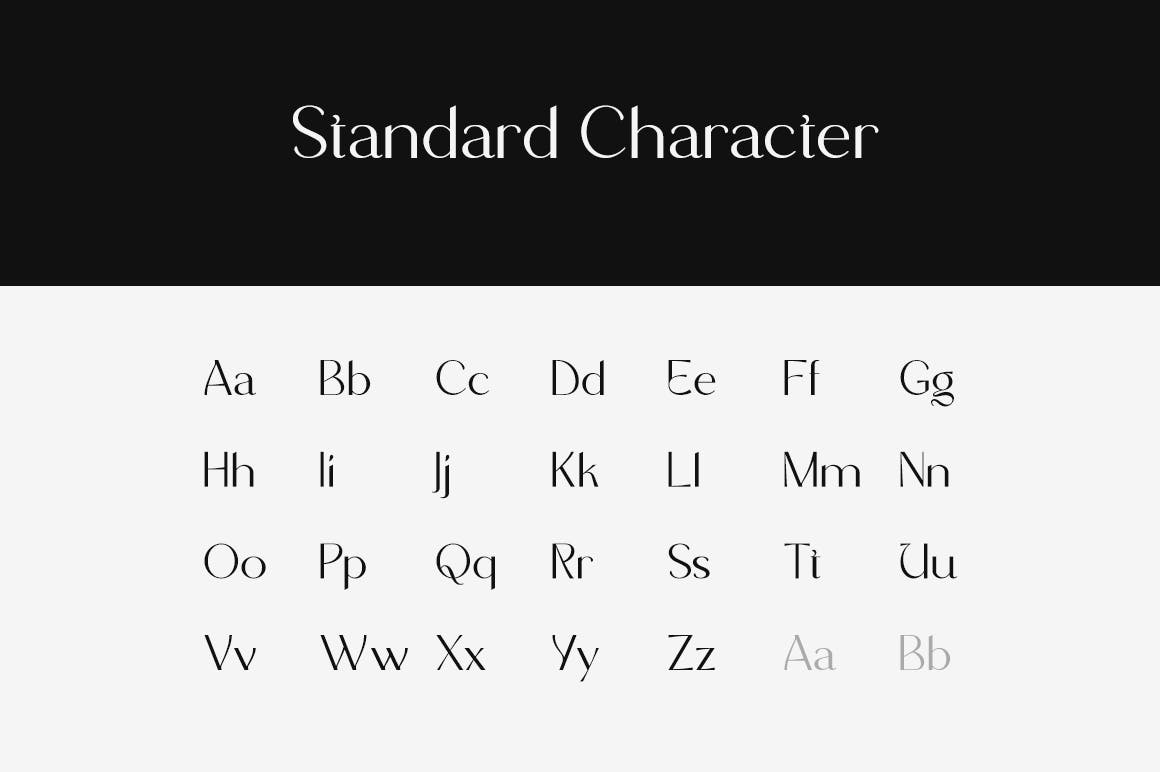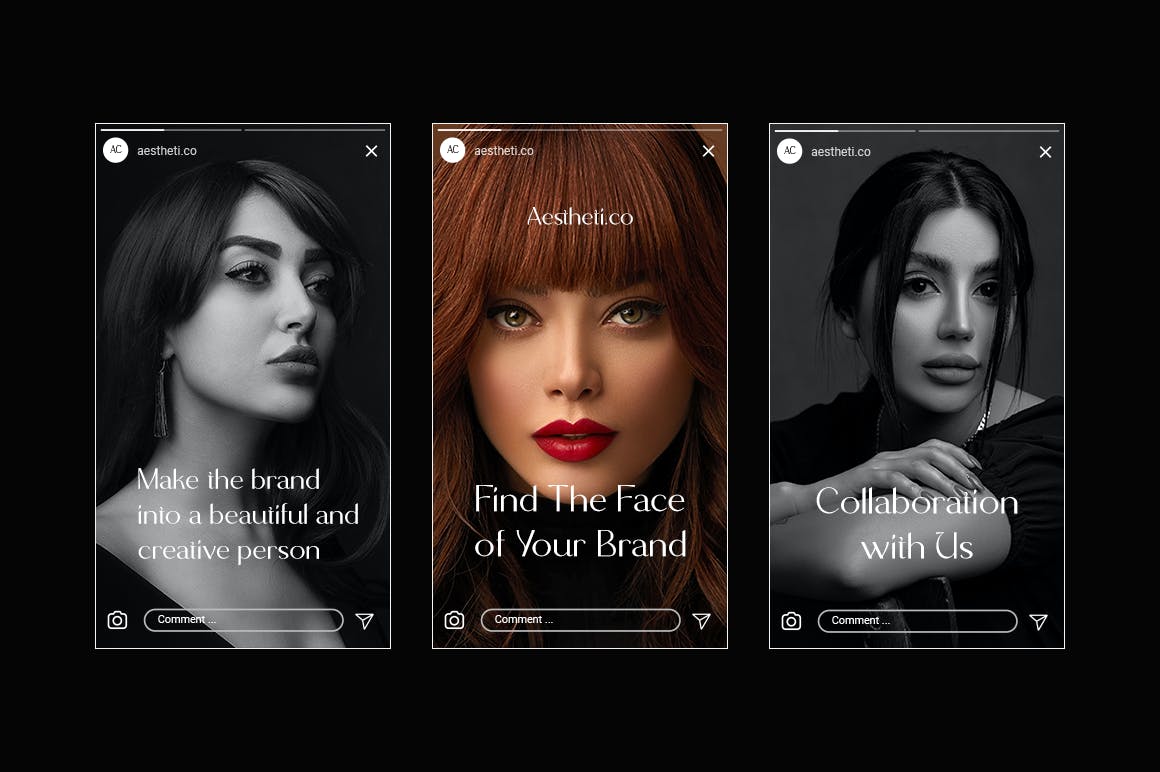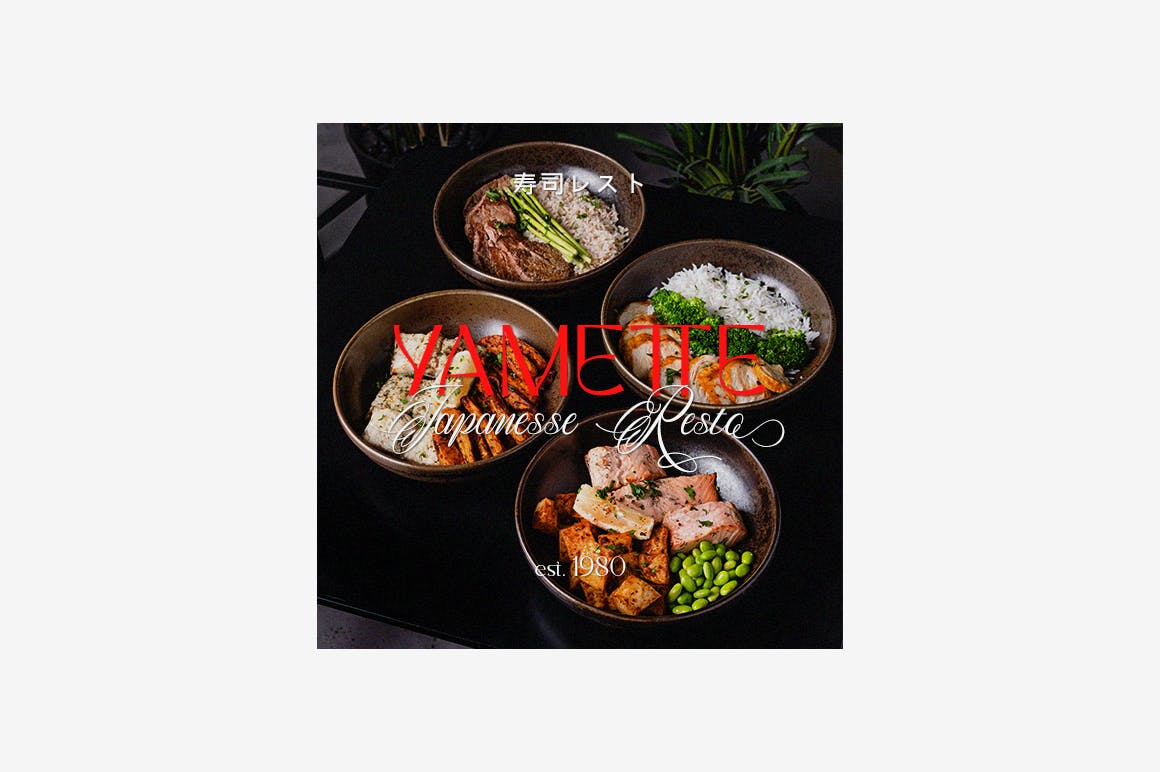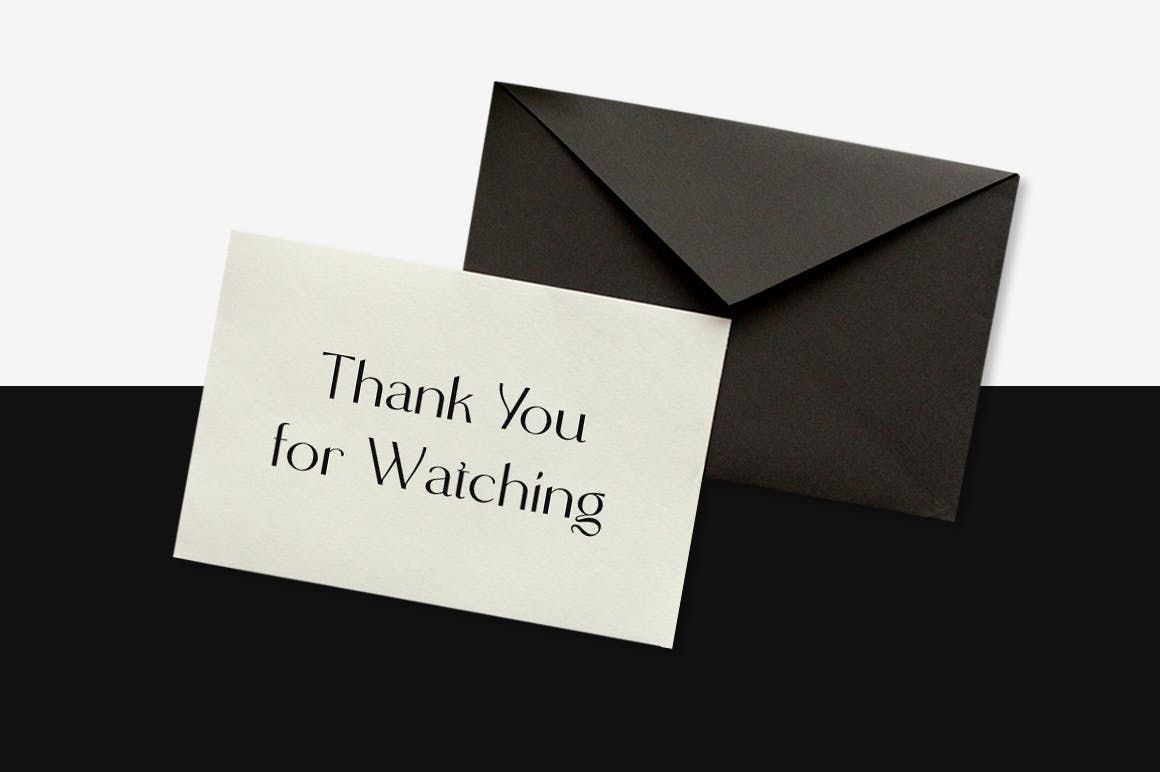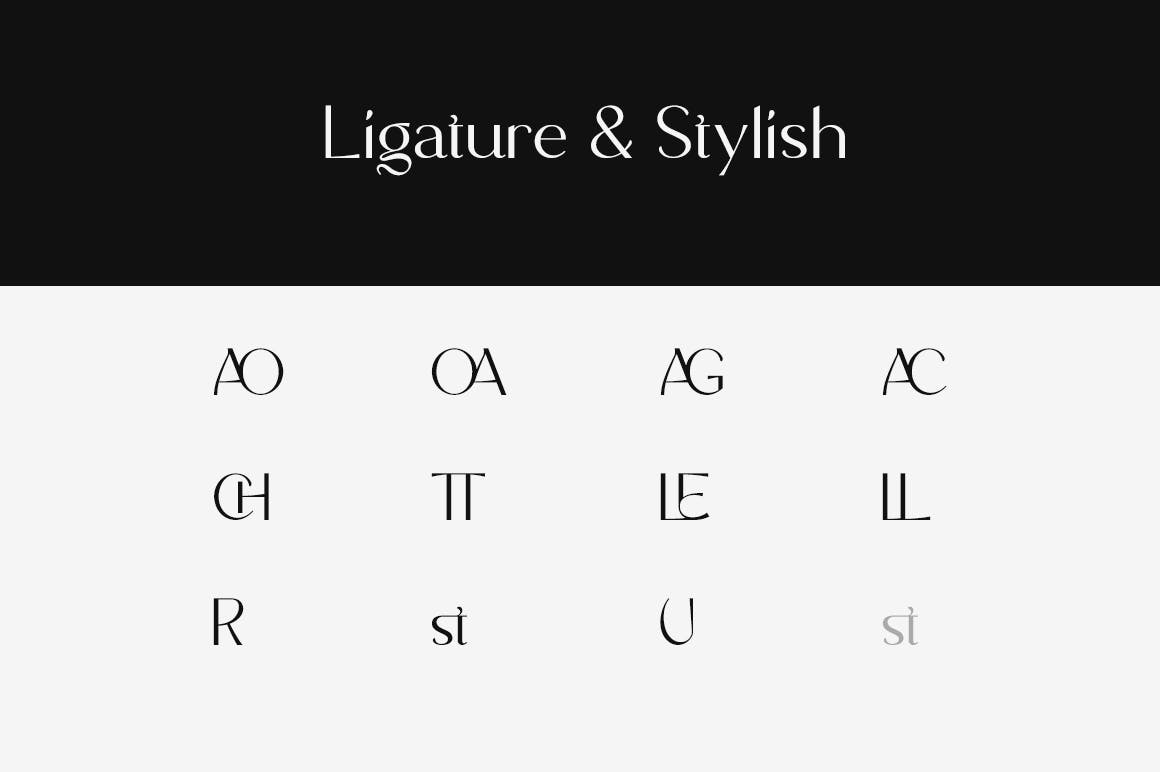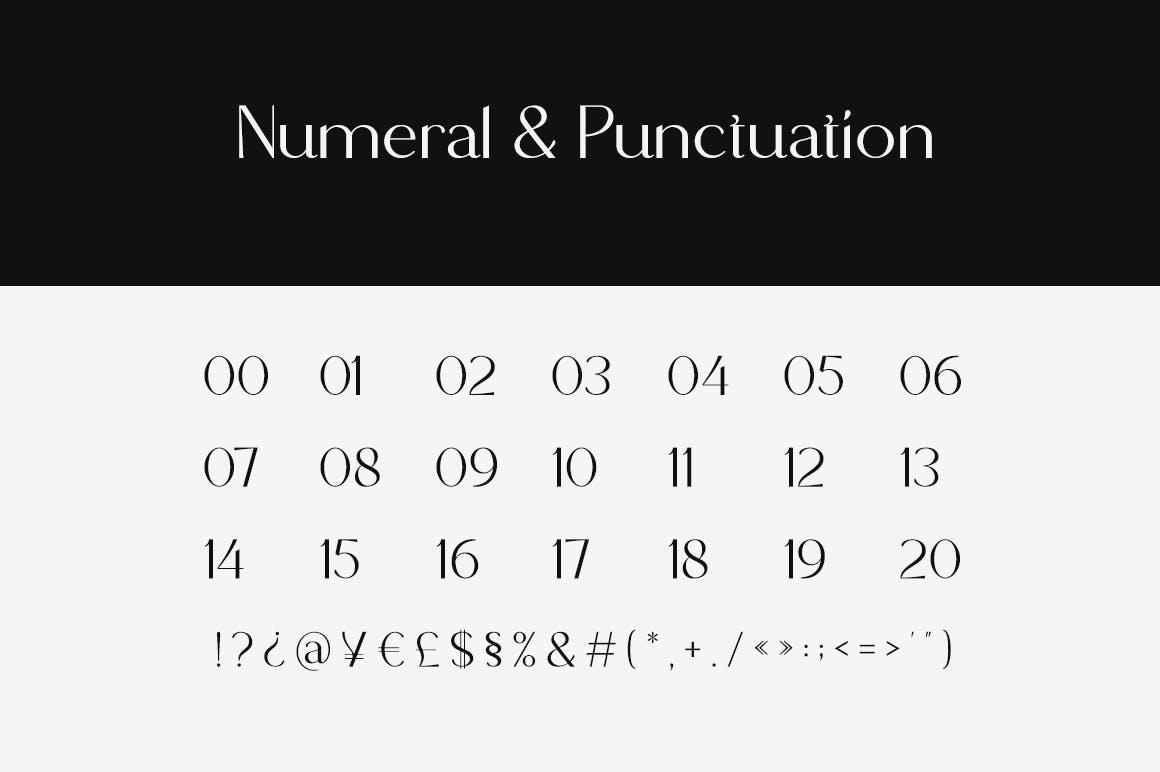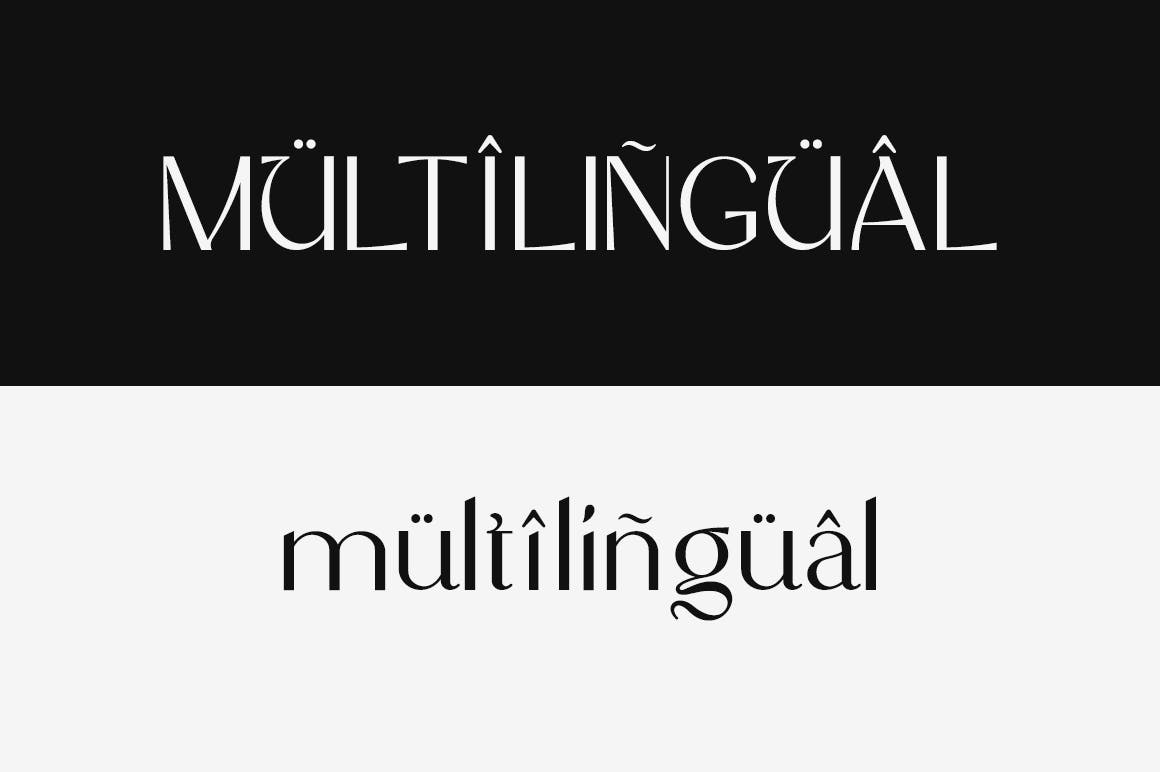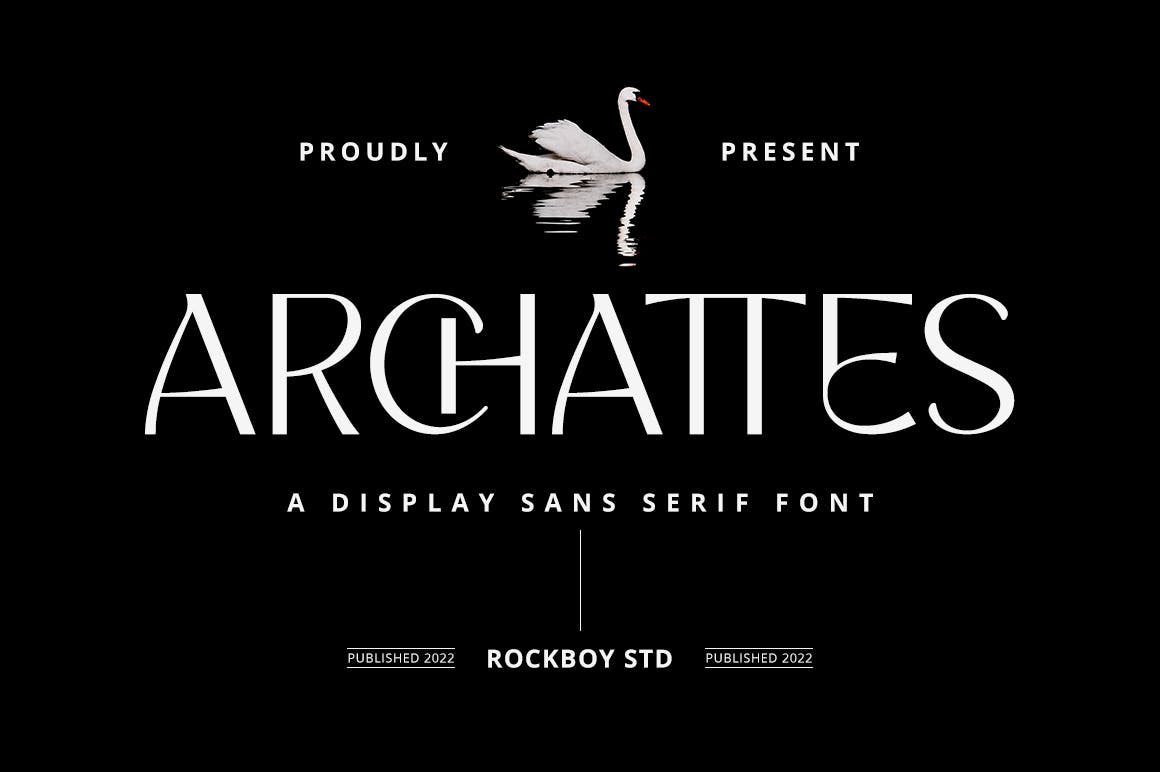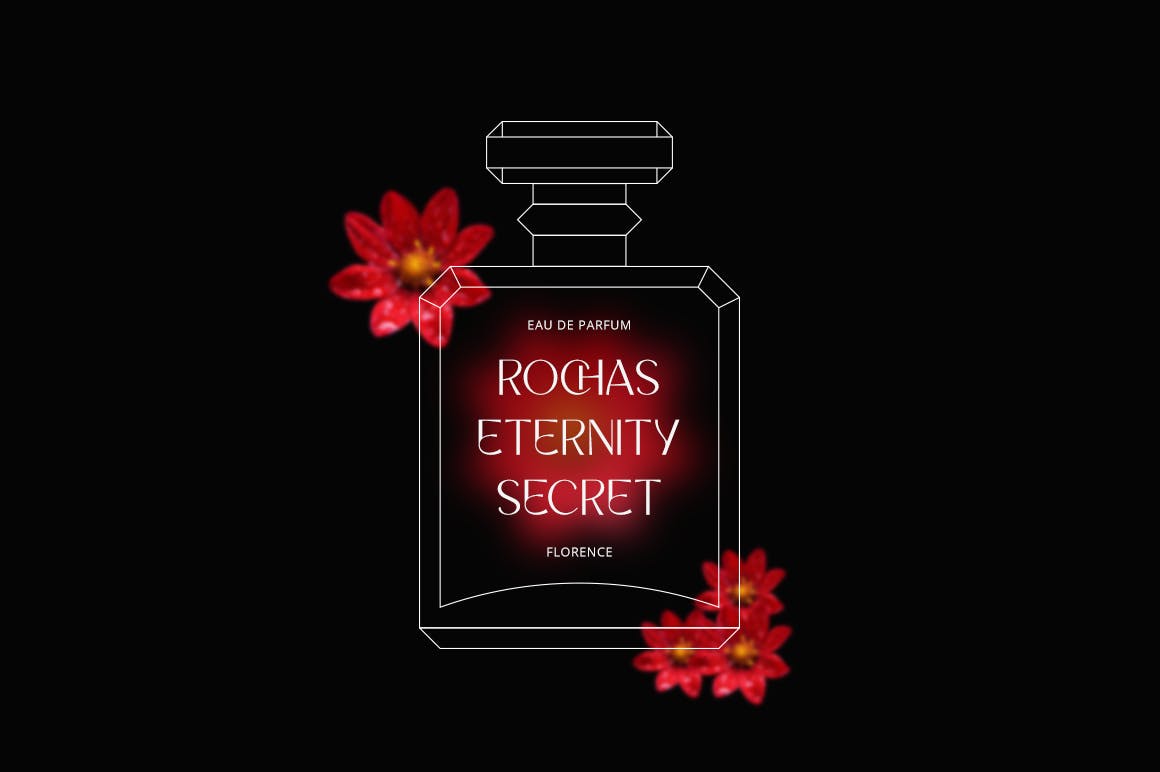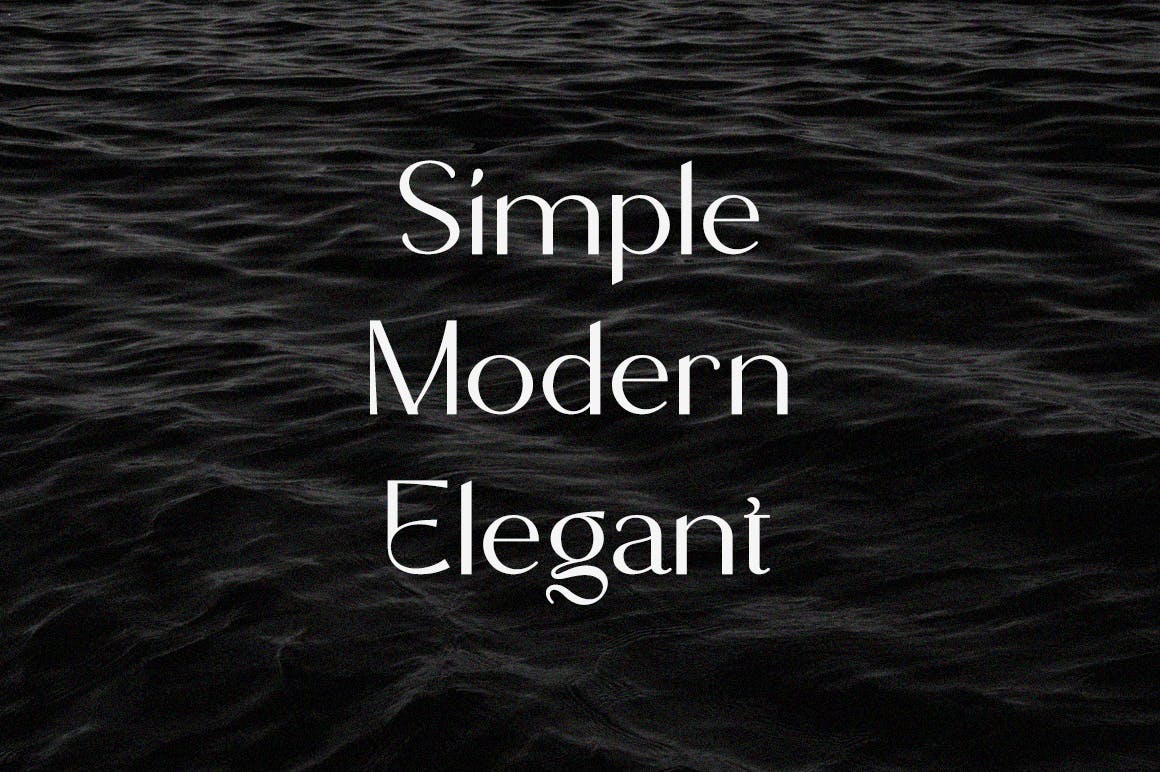
Archattes یک فونت زیبا و شیک از نوع سنس سریف است که میتواند ایدههای خلاقانه شما را به سطح جدیدی برساند. این فونت برای انواع پروژهها از جمله کارتها، برندینگ، برچسبها و بسیاری دیگر مناسب است. با افزودن این فونت به پروژههای خود، طراحیهای خود را فوقالعاده کنید!